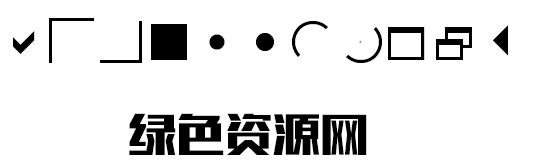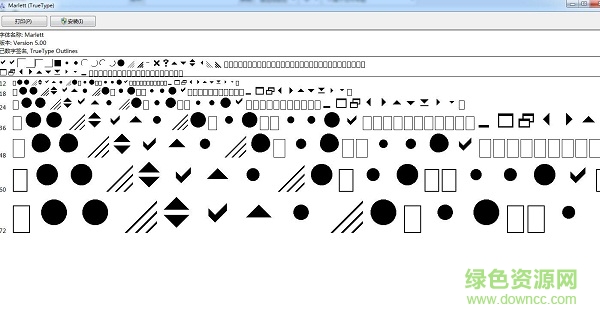
marlett字體
marlett是什么字體?marlett.ttf字體是一款適用于win7系統(tǒng)的符號字體,輸入字母或數(shù)字都可以打出不同的符號,包括圓圈、對號、問號以及各種不規(guī)則的圖案,有需要者歡迎下載使用!
marlett字體介紹
它是Windows的系統(tǒng)字體之一,開始菜單中的“4 ”,窗口右端的最大化、最小化、還原、關(guān)閉按鈕,單選、復(fù)選框前的“√”,以及用于狀態(tài)條中的“5 6 ”等等,都是用該字體建立的。此字體不能刪除,否則前述符號都將變?yōu)閿?shù)字形式。